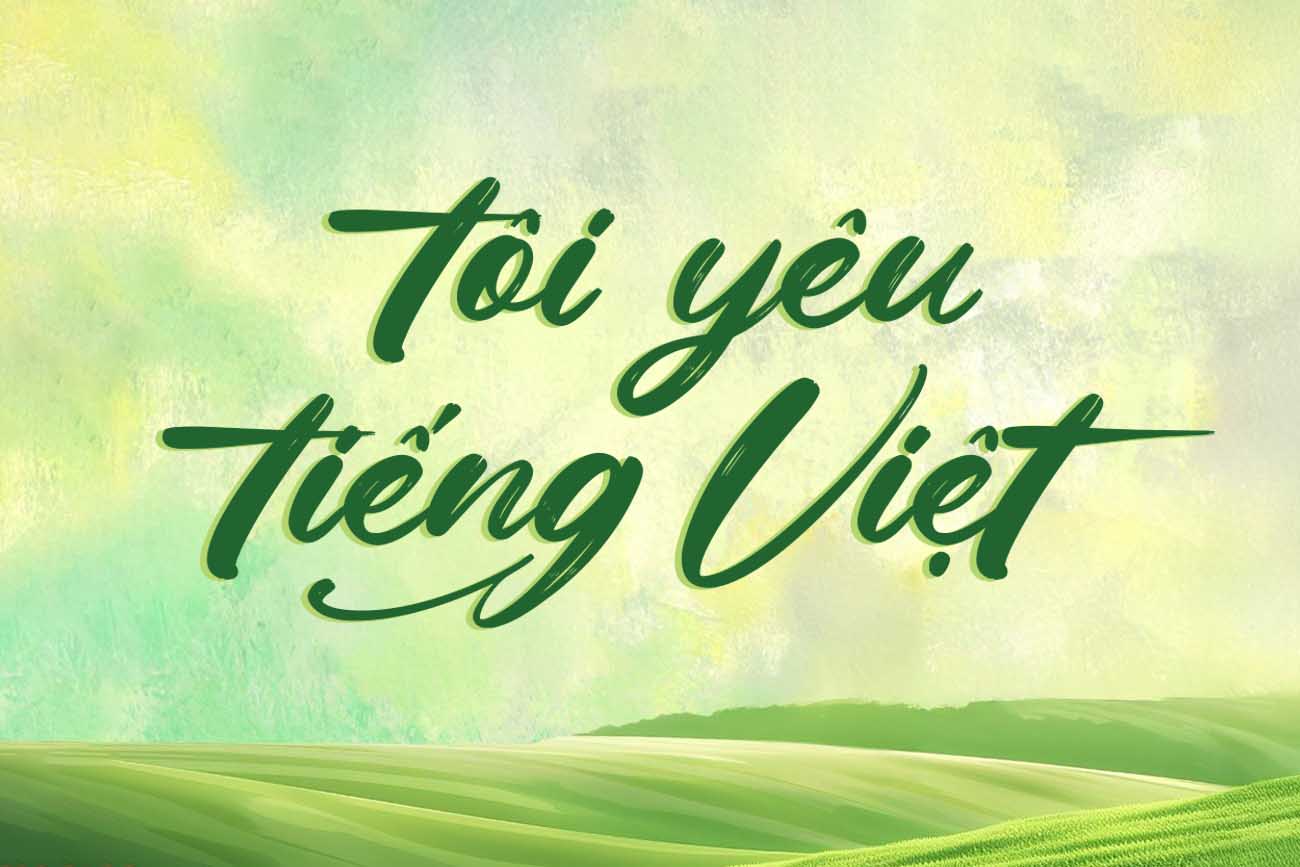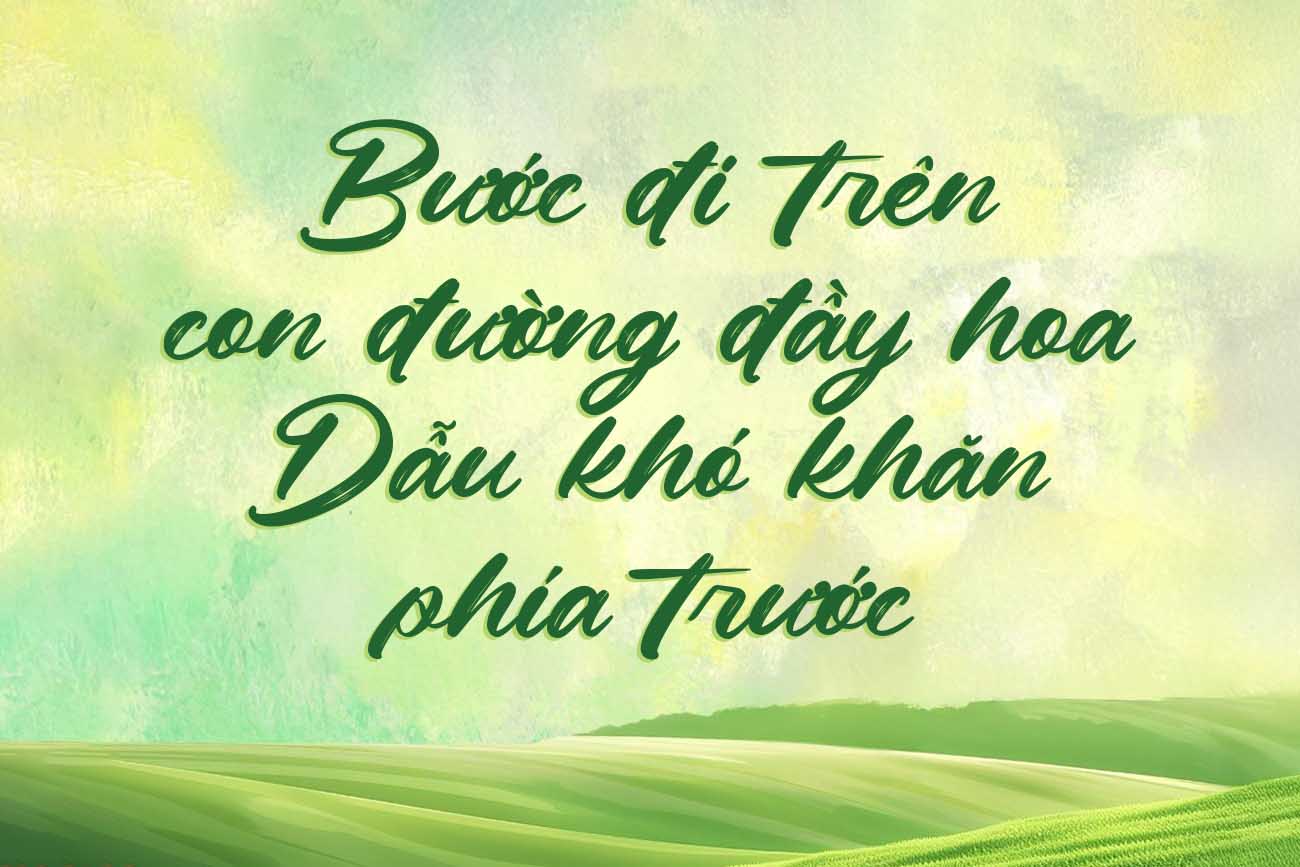
Tác giả Rian Hughes
Giới thiệu tổng quan
Trong thế giới thiết kế đương đại, font brush, hay còn gọi là font nét cọ – luôn là lựa chọn yêu thích nhờ vẻ ngoài phá cách, mạnh mẽ và đầy tính nghệ thuật. Một trong những font nổi bật thuộc nhóm này chính là Kinetic Motion. Được thiết kế bởi Rian Hughes và Việt hóa cẩn thận bởi Phạm Sơn, font chữ này mang đến cảm giác chuyển động sống động như những nét cọ đầy năng lượng, đặc biệt phù hợp cho các thiết kế hiện đại và kỹ thuật số.
Với phiên bản font Việt hóa đầy đủ, Kinetic Motion không chỉ đẹp về mặt hình thức mà còn sẵn sàng sử dụng cho mọi nội dung tiếng Việt mà bạn cần.
1. Kinetic Motion – Font Chữ Brush
Khác với những font sans-serif cứng nhắc, Kinetic Motion là một font brush mang kiểu dáng nét cọ mạnh mẽ kết hợp cùng bố cục hình học tinh tế. Đặc điểm nổi bật của font này nằm ở:
• Nét nghiêng chuyển động: Các ký tự có độ nghiêng nhẹ về phía trước như đang lao nhanh về phía trước – đúng chất “motion”.
• Đường nét như vẽ bằng cọ: Tạo cảm giác tự do, phóng khoáng nhưng vẫn rõ ràng và dễ đọc.
• Hình học khỏe khoắn: Gợi sự hiện đại, chính xác, rất phù hợp với công nghệ, kỹ thuật số.
Với thiết kế đặc biệt như vậy, Kinetic Motion có thể coi là sự giao thoa hoàn hảo giữa font brush nghệ thuật và font hiển thị chuyên nghiệp.
2. Bản Việt hóa chất lượng bởi Phạm Sơn
Phiên bản font Kinetic Motion Việt hóa được thực hiện bởi Phạm Sơn, một nhà thiết kế uy tín trong cộng đồng font Việt.
Ưu điểm của bản Việt hóa:
• Đầy đủ dấu tiếng Việt: Bao gồm tất cả chữ có dấu, thanh điệu, chữ cái đặc biệt – tương thích với mọi nội dung tiếng Việt.
• Giữ nguyên tinh thần brush: Dù thêm dấu nhưng vẫn bảo toàn độ nghiêng, nhịp điệu, và nét cọ tự nhiên của font gốc.
• Không lỗi font: Hiển thị tốt trên mọi phần mềm thiết kế như Photoshop, Illustrator, Canva, Figma...
Bản Việt hóa không chỉ chuyển đổi ngôn ngữ mà còn bảo toàn tinh thần sáng tạo ban đầu, giúp designer Việt có thêm công cụ độc đáo và giàu cảm xúc.
3. Ứng dụng nổi bật của font brush Kinetic Motion
Là một font brush Việt hóa mang phong cách chuyển động, Kinetic Motion mở ra nhiều cơ hội sáng tạo trong thiết kế:
Thiết kế tiêu đề & poster
• Hoàn hảo cho tiêu đề game, phim hành động, giải đấu thể thao.
• Tạo hiệu ứng “chuyển động nhanh” ngay trong con chữ – không cần hiệu ứng phụ.
Branding cá tính
• Dùng cho logo startup công nghệ, app mobile, nhãn hàng năng động.
• Gợi phong cách mạnh mẽ, tiên phong, phù hợp các thương hiệu trẻ.
Giao diện UI/UX & Social Media
• Tăng tính sinh động cho các landing page, giao diện tương tác.
• Dễ đọc nhưng không nhàm chán – điều hiếm có ở nhiều font brush khác.
Kinetic Motion là một lựa chọn font brush đầy cảm hứng cho bất kỳ nhà thiết kế nào yêu thích nét cọ năng động, hiện đại và cá tính. Phiên bản Việt hóa bởi Phạm Sơn càng nâng cao giá trị ứng dụng trong cộng đồng sáng tạo tại Việt Nam – từ thiết kế poster, tiêu đề, thương hiệu đến giao diện số.